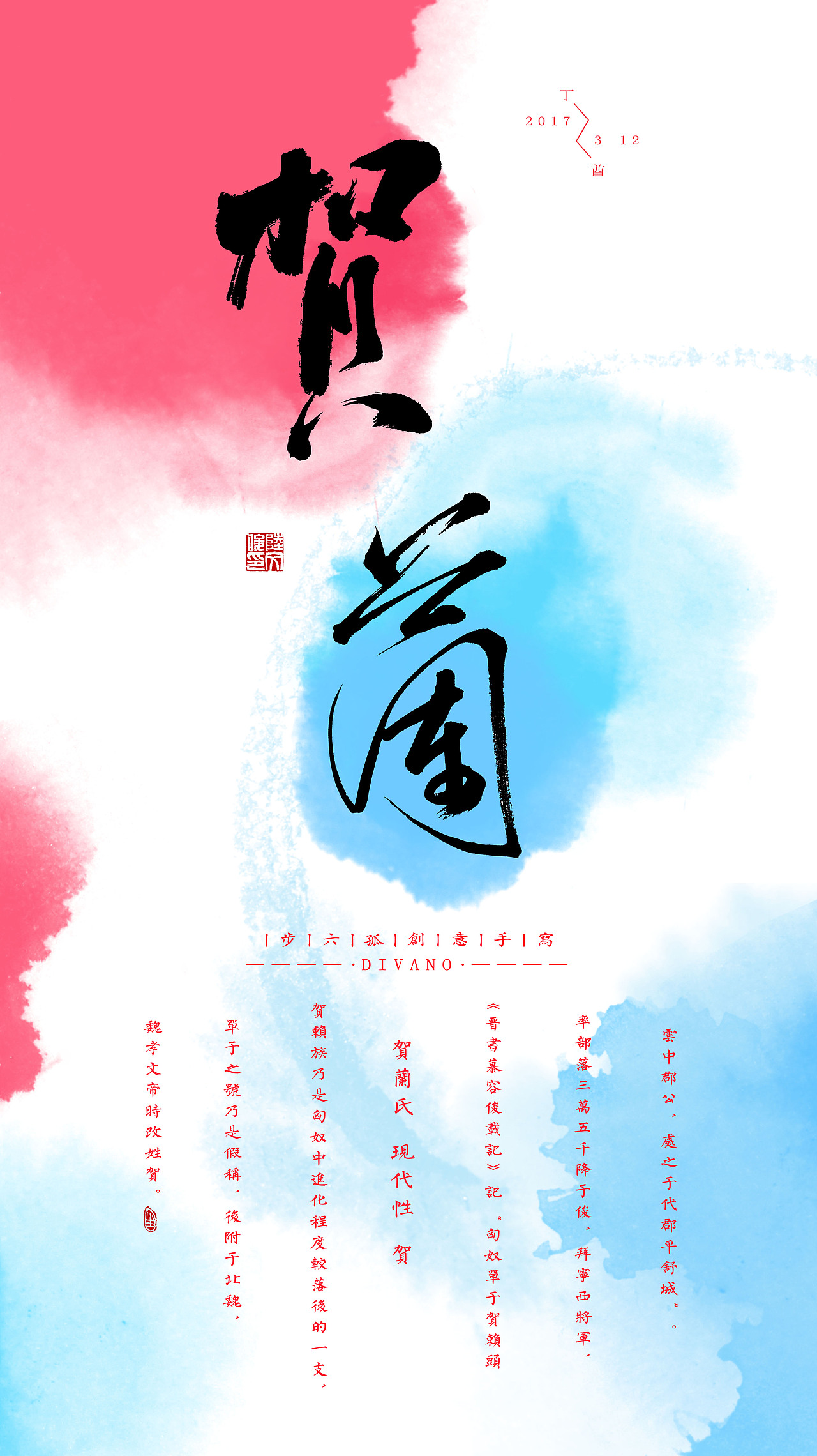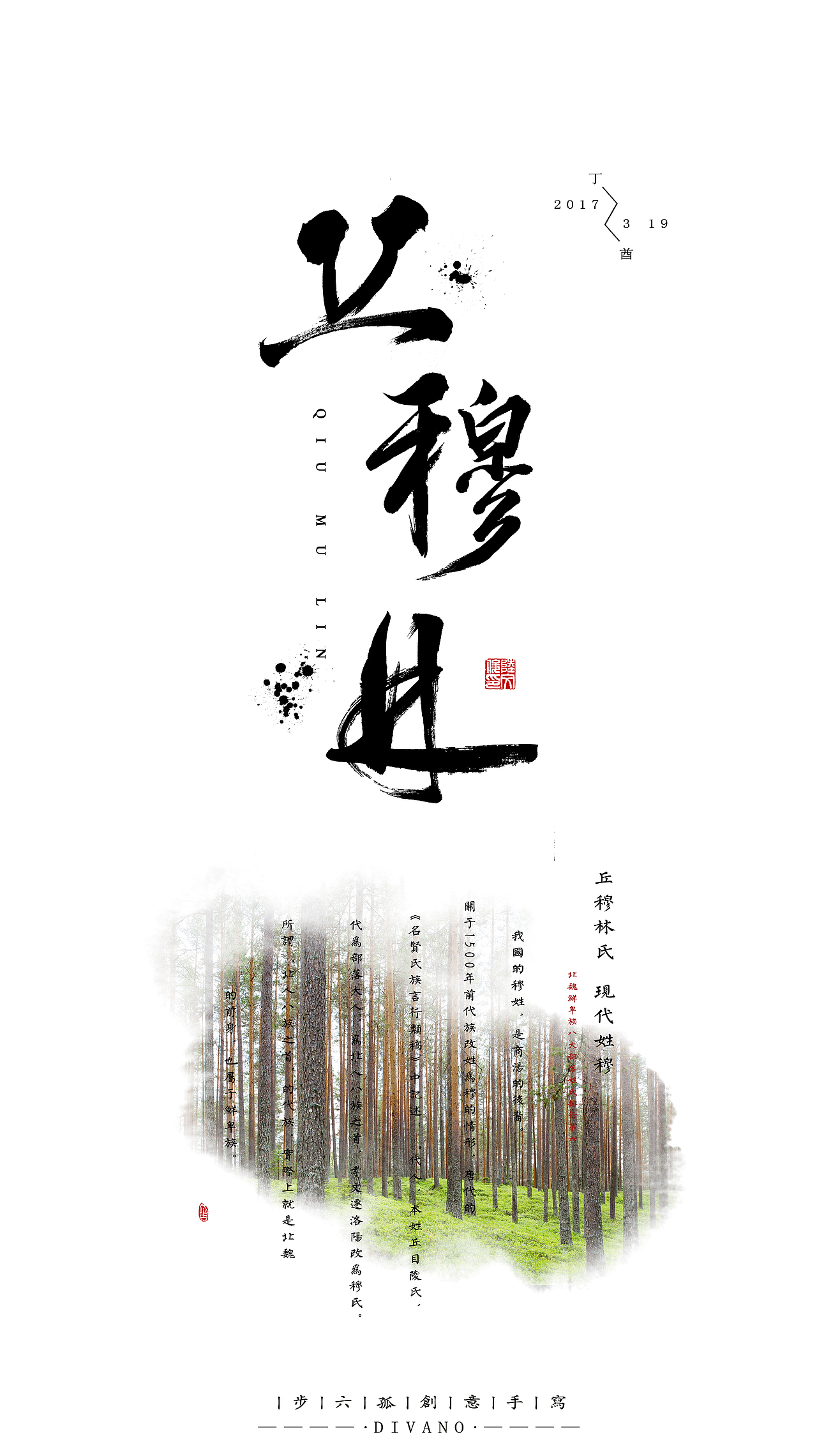
丁酉年 六孤原创手写集之鲜卑八大姓氏
本人是学平面设计的学生小白一枚,早在一年之期,大一的时候就已经有想法,把自己的书法和设计结合。自从接触了站酷的各种书法字体设计的大神之后,迫不及待,于是乎,就有了写一本书法集子的打算,说是书法集子,其实只是一本练习稿子,哈哈。希望大家互相交流,一起进步~
一开始想要创作书法,正琢磨着写什么好的时候,突然让我想起了中学历史课本里的一个很特别的姓——步六孤,我仔细百度一番之后,发现原来还有除了步六孤之外的8个姓,于是,我便产生了写一本系列集子的打算。
在创作的同时,我也买了一些书法字体设计的书一边学习,一边想着把书本的东西运用到我的创作里面。书里面讲得挺好,可是呢,毕竟是第一次做创意型的字体设计,其实感觉还是很难打破以前写书法的那种固定的模式和羁绊。我开始逐渐意识到,我们平时写书法玩玩跟把书法写出来做设计,可能是两回事,书法仅仅追求视觉美感,而书法设计要讲求创意和创新。
我一直都坚信,每一个字都有灵魂,所以,在书法设计里面表现出我个人的思想,一直都是我在努力追求的东西。
而这一次的练习,并没有我想象中那么完美,我感觉我仅仅表现出了书法的视觉美感,却没有表现出字体背后的那段传奇般的历史故事。
八姓之上的皇姓
步六孤
贺兰
独孤
贺楼
忽忸于
丘穆林
纥奚
尉迟